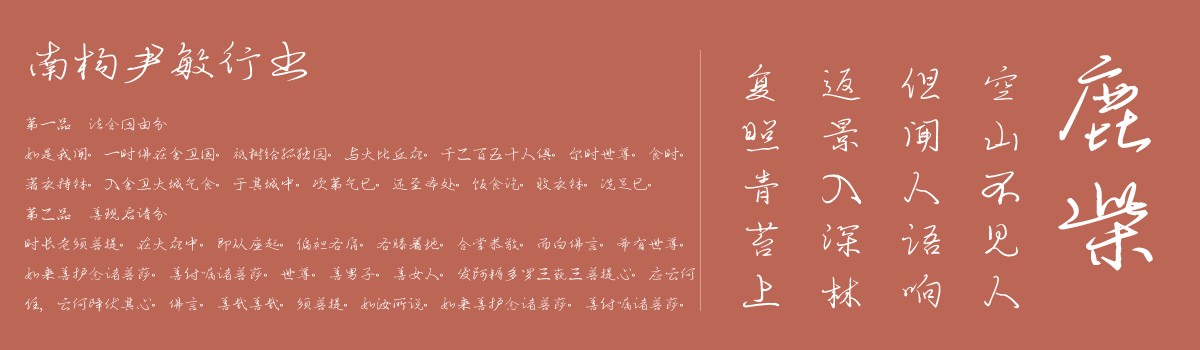
南构尹敏行书
这款字体是有尹敏书写,字体家平台南构字库独家制作发行的字体,手写体风格,适合用于BLOG设计,轻画面设计等应用。
作者简介
叫尹敏,36岁,在一家较知名的房企里做设计经理,是一名外表年轻、心态更年轻的文艺青年。六年前当我下定决心去培养几项长期的兴趣爱好来开始养生,改善自己生活品质的时候,我深思熟虑而又毅然决然的选择了书法作为其中一项(其他几项是象棋、诗歌、游戏等,兴趣广泛,同予者何人?),并兴趣浓烈的坚持了下来。在几次长达数月的逍遥的日子里,每天练字长达十数小时,几乎除了睡觉,醒来就念叨切磋着书法。心驰神往,悠悠然有魏晋名士般的倜傥不羁情调。身处闹市,这何尝不是对身心压力的奢侈纯粹的疏解?……扯远了。
我很爱书法,就像我爱我的娃。我有一个两岁的娃,虽然我三十岁之前没练过字,但现在练好字并启发孩子是我一个心愿和动力,我自己在书法上也将有着较高的追求。练字目前于我的意义,就是让自己每天充实快乐,并隔上一段时间能看见一点进步。这就像现在的生活,一个男人养活一家三口是有些难和累,但一月月一年年的微笑走来,会渐渐接近想要的幸福,接近诗和远方。我最近数月的工作忙的有点杂乱无章了,一两周才练一两次字了,心中却忘不了曾经沉醉书法的状态。我会调整自己,每一两年沉醉的练习书法数月,提升书法水平,并更新我的字体库。当我几年后实现我的短期奋斗目标,无现实压力的练字的时候,我想那将会是我倍加珍惜的时光吧!愿与有志于书法者共勉。